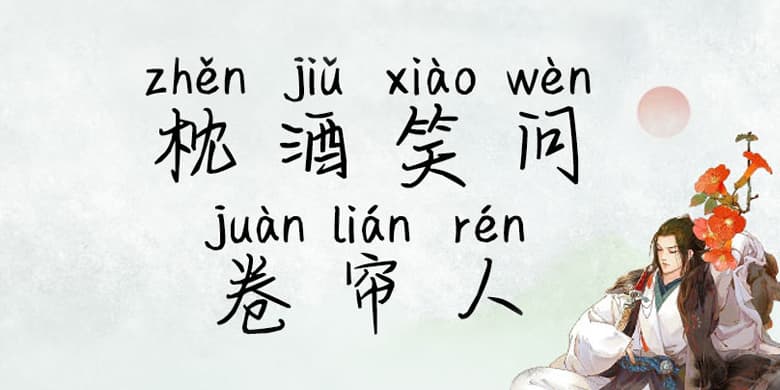
品牌:方正手迹设计师:余丹发行时间:2020字库编码:大陆简体(GB2312-80)分类:常规书写·硬笔字体属性:精品字
枕酒笑问卷帘人是一款拼音体,汉字部分在气质上,具有一股积极向上的生命力与坚韧不拔的毅力。是一款充满正能量的字体。适用于文艺类的书刊、品牌广告和产品包装设计,以及社交网络的个性化用字。